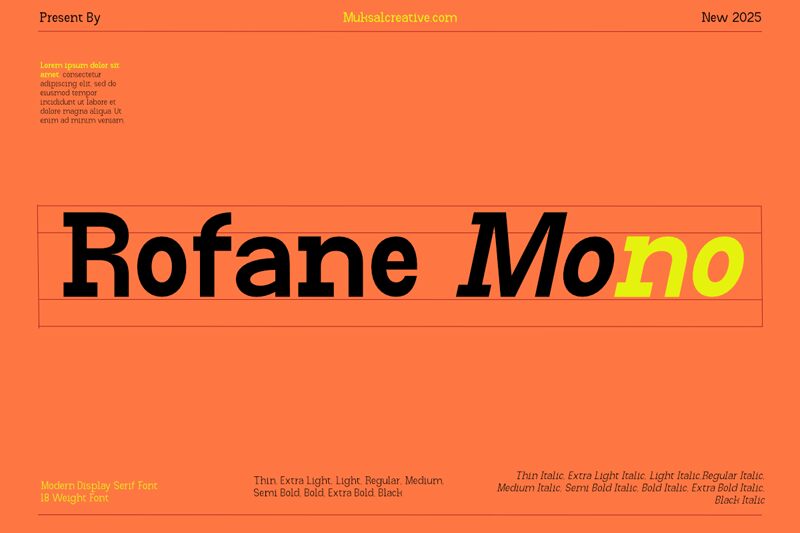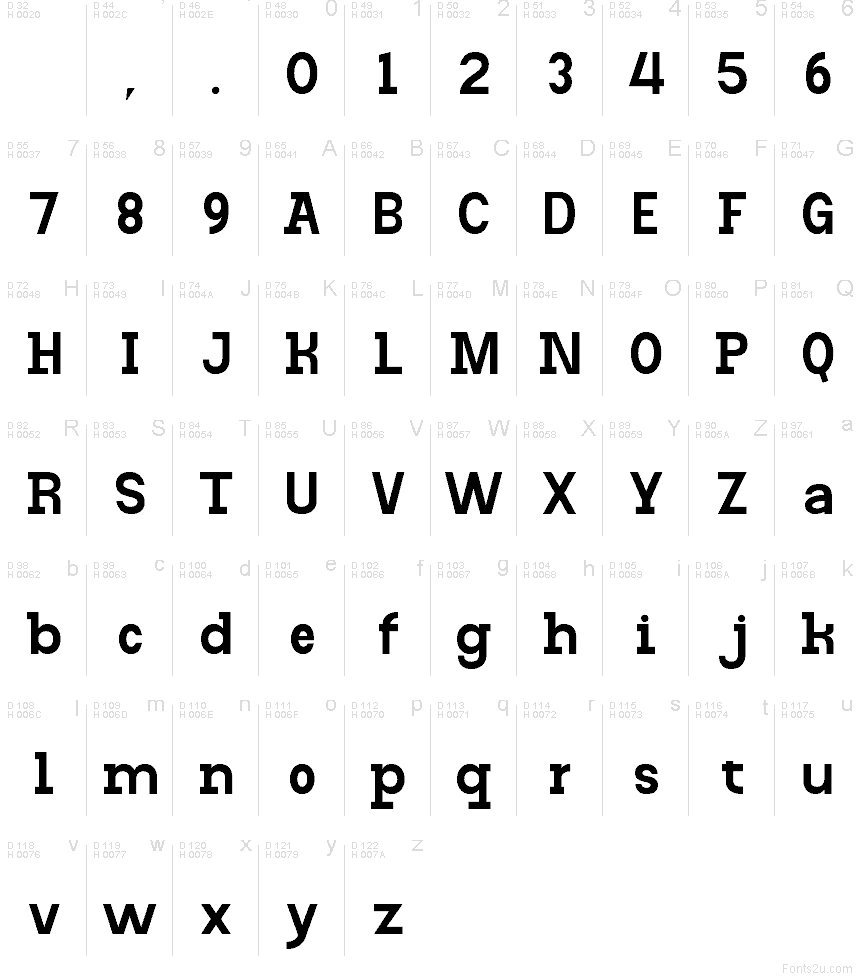
Rofane Mono Semi Bold
Rofane Mono Semi Bold od Muksal Creative je bezplatné monospaced písmo bez pätiek, so zaoblenými rohmi a jemnou geometrickou štruktúrou. Písmená pôsobia pevne a rovnomerne, so širokými kruhovými tvarmi a rovnými stranami, ktoré udržiavajú konzistentný rytmus v celom texte.
Rofane Mono Semi Bold je bezplatný font, ktorý sa skvele hodí na návrhy log, titulky plagátov, technické označenia, rozhrania a krátke nápisy. Stabilné rozostupy a zmäkčené hrany dodávajú týmto aplikáciám úhľadný a výrazný vzhľad bez pocitu tuhosti alebo nadmernej ozdobnosti.